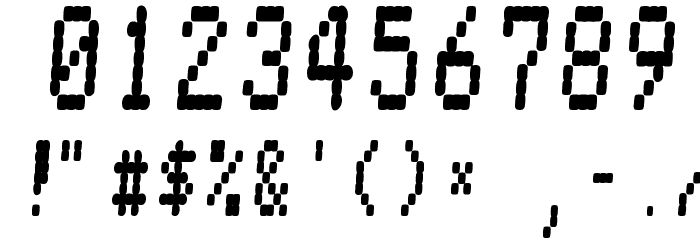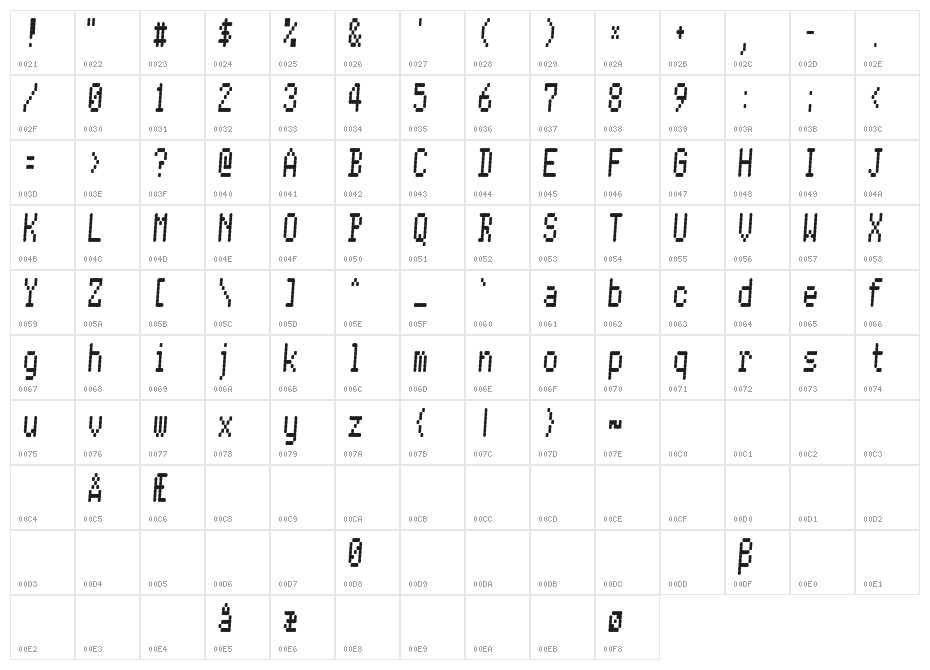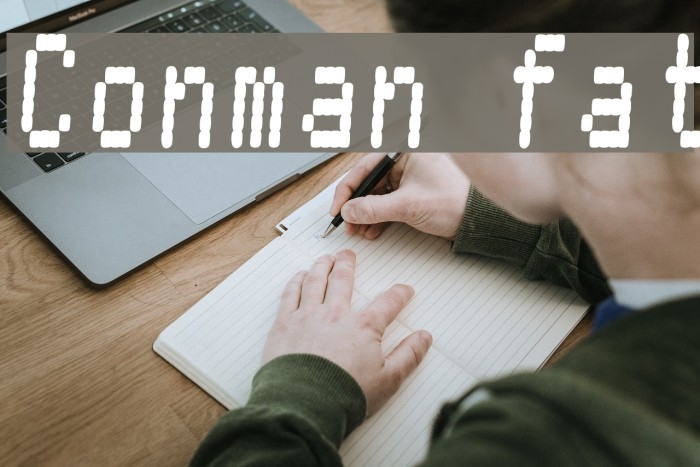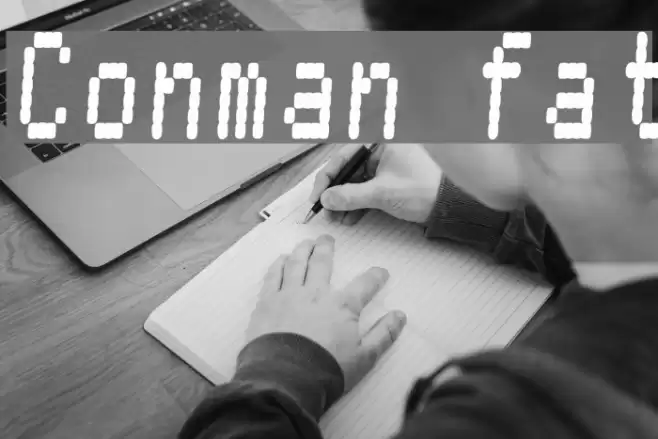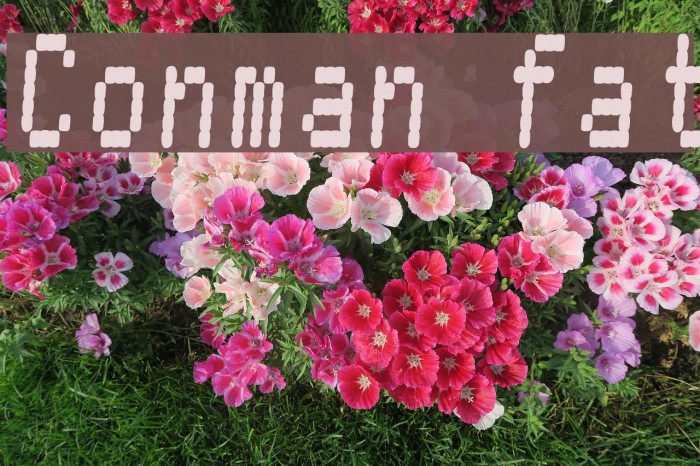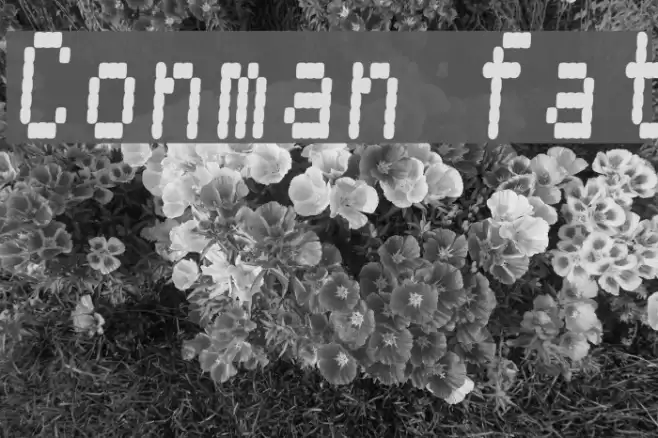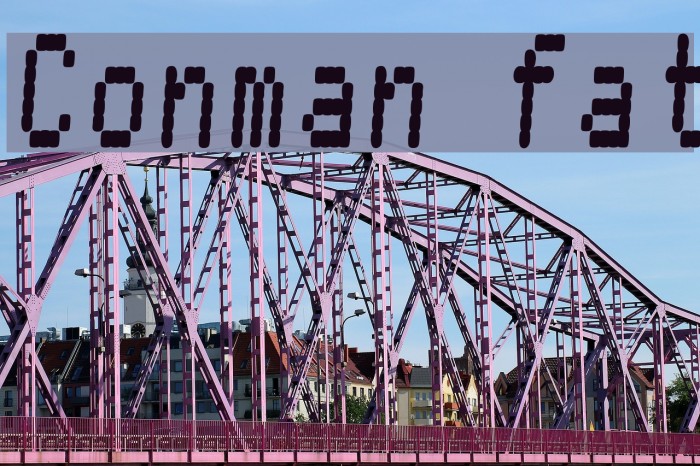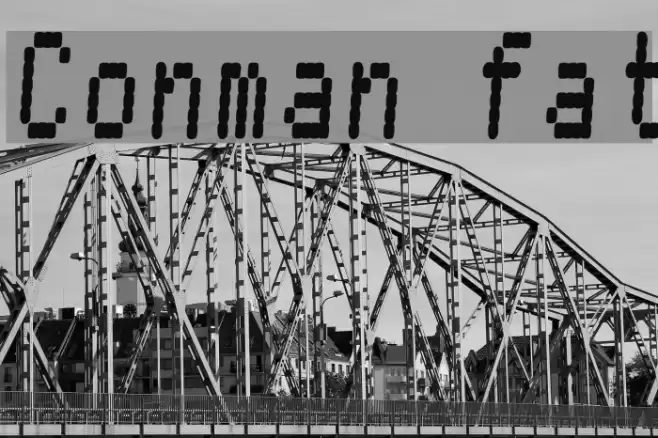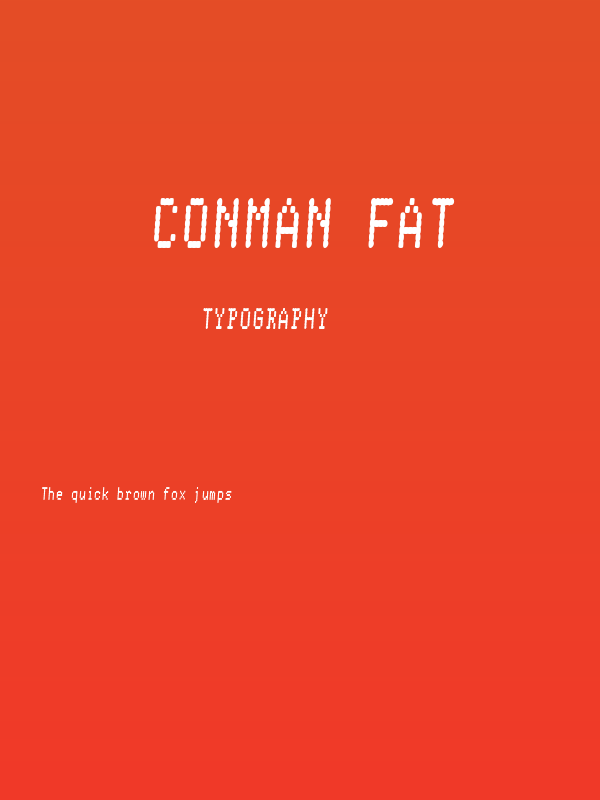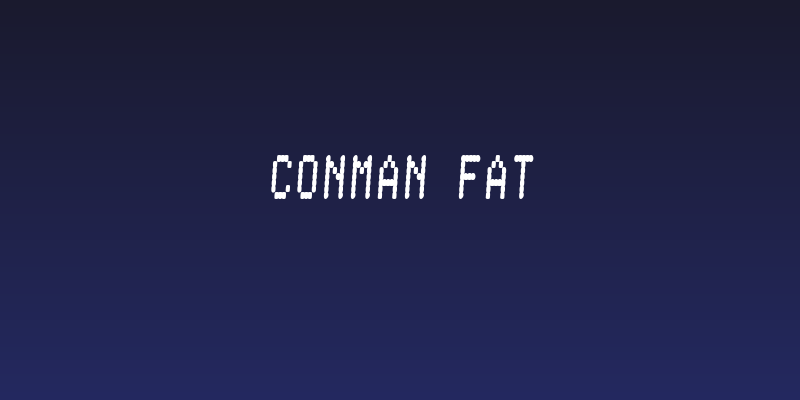
Conman fat Font
✎ Pixel
CONMAN-FAT 大文字
CONMAN-FAT 小文字
CONMAN-FAT その他の文字
| 名前 | Conman fat |
| カテゴリ | Pixel |
| 全体的なスタイル | Retro, Digital |
| おすすめプロジェクト | Ideal for digital-themed projects, retro video games, tech-related branding, or any design requiring a nostalgic, digital look. |